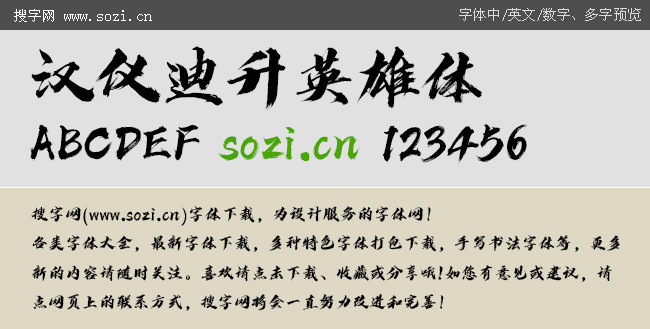
漢儀迪升英雄體
搜字網(wǎng)給大家提供一款漢儀迪升英雄體中文字體下載,漢儀迪升英雄體筆觸豪放,字跡飛揚(yáng),洋洋灑灑,曲中帶剛,道勁有力,松弛有度,形神兼具,有一瀉千里,氣吞山河之勢。筆畫豪放,飽滿而富有彈性,空間感十足。適用于游戲頁面或中國風(fēng)電影海報等眾多設(shè)計場合。。(本字體為個人非商用版,如需要商用請聯(lián)系漢儀公司購買版權(quán))